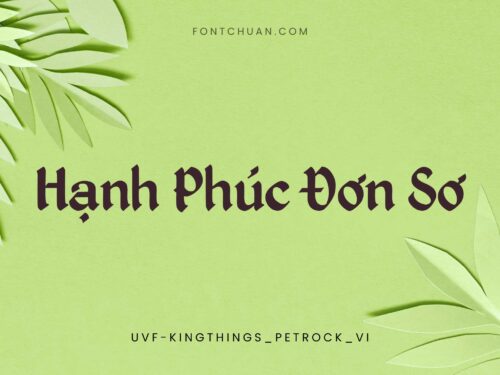
Font Decorative
Font Decorative, font dùng trang trí sáng tạo và độc đáo
Font Decorative là nhóm font chữ chuyên dùng cho mục đích trang trí, mang đến phong cách thiết kế đầy nghệ thuật và cá tính. Không giống như font serif hay sans-serif thông thường, font Decorative có thiết kế đặc biệt với các chi tiết tinh xảo, biến tấu đa dạng, giúp làm nổi bật nội dung trong các thiết kế sáng tạo. Các font này thường được sử dụng trong tiêu đề quảng cáo, bao bì sản phẩm, thiết kế thiệp, bìa sách, poster sự kiện hoặc các dự án nghệ thuật.
Nhiều bộ font Decorative đã được nhóm Việt hóa để đảm bảo hiển thị tốt tiếng Việt mà vẫn giữ nguyên phong cách thiết kế gốc. Một số font tiêu biểu bao gồm iCiel Lemon Jelly – font chữ bubble đầy màu sắc, SVN-Wonderland – mang phong cách cổ tích huyền bí, hay UTM Garamond Fancy – kiểu chữ serif với nét hoa mỹ trang trí.
Bộ sưu tập Font Decorative tại Font Chuẩn hiện có hơn 120 kiểu chữ khác nhau, trải dài trên nhiều phong cách như hand-drawn decorative mang nét vẽ tay tự nhiên, vintage decorative với họa tiết cổ điển, và modern abstract với thiết kế sáng tạo. So với các font sans-serif tối giản, font Decorative có tính thẩm mỹ cao và mang lại hiệu ứng thị giác mạnh mẽ, giúp nội dung trở nên sinh động và thu hút.